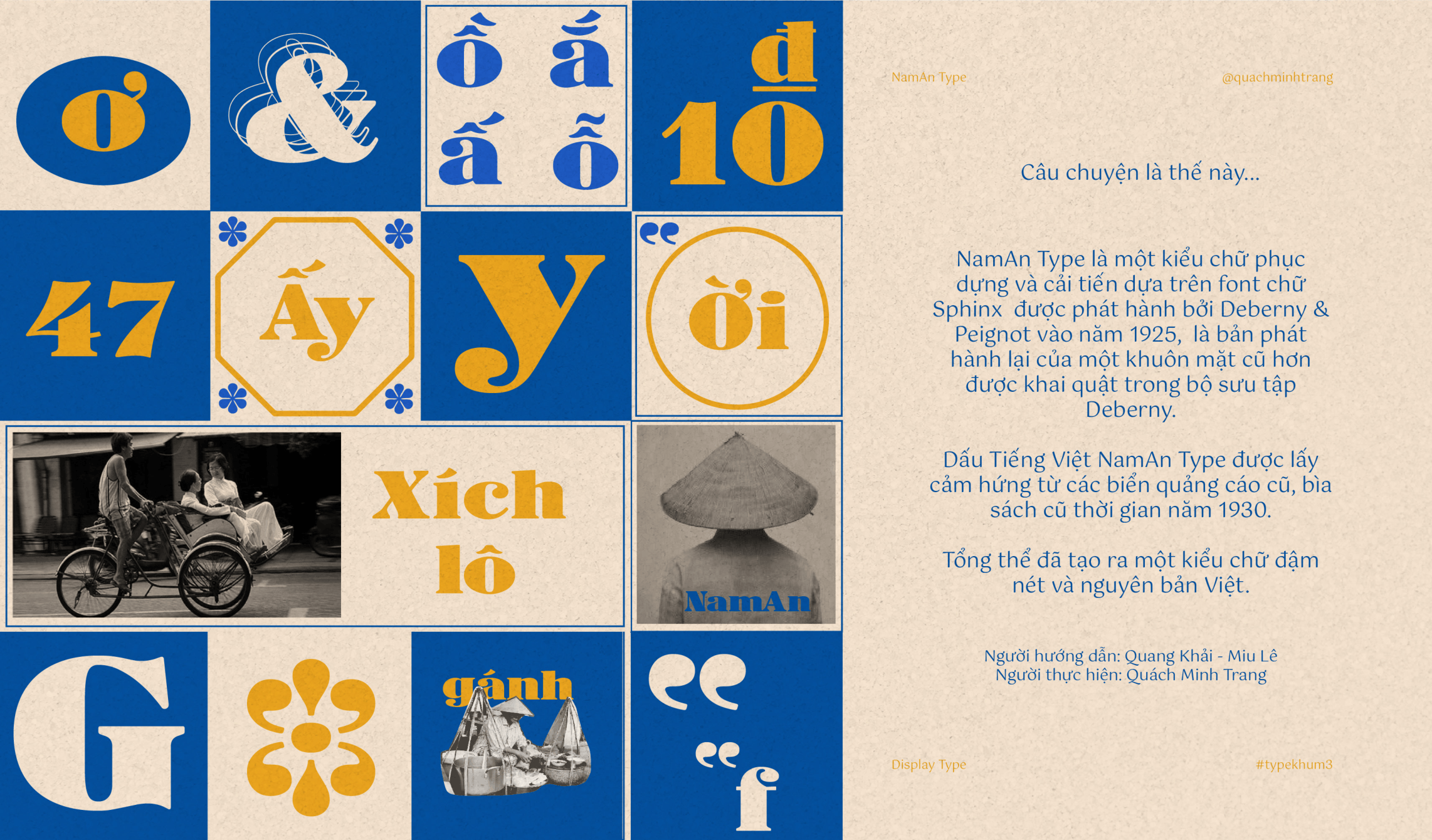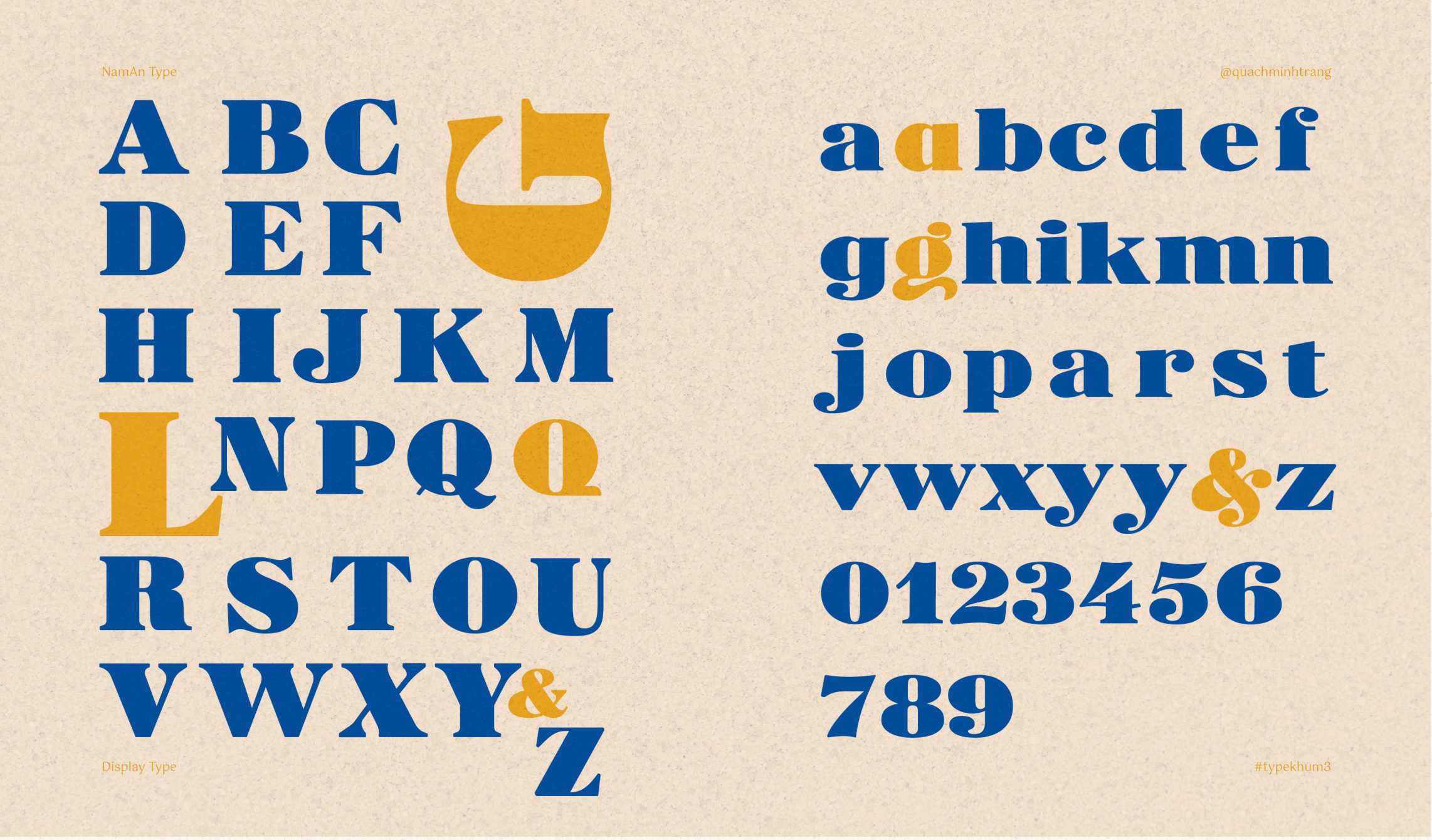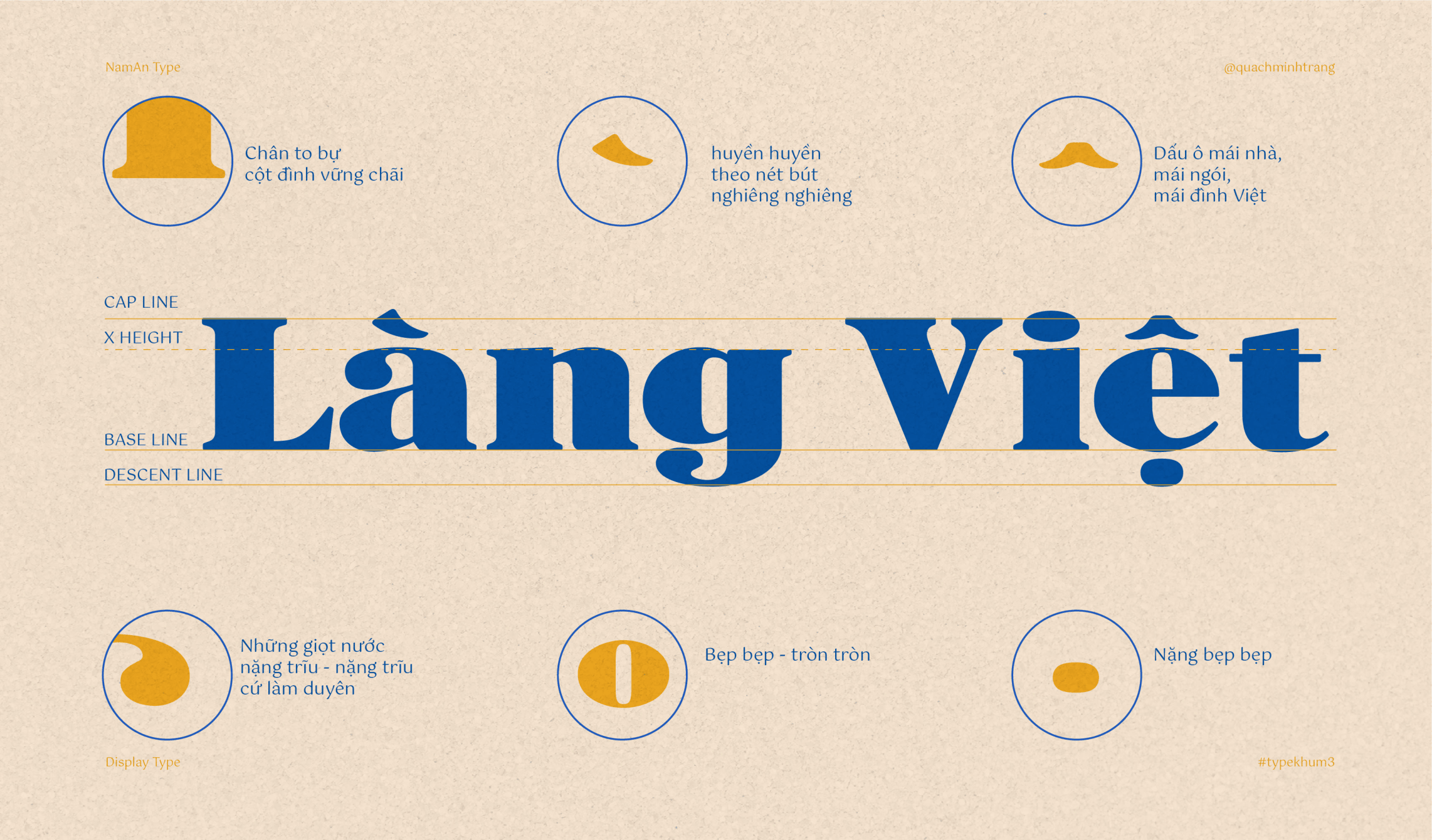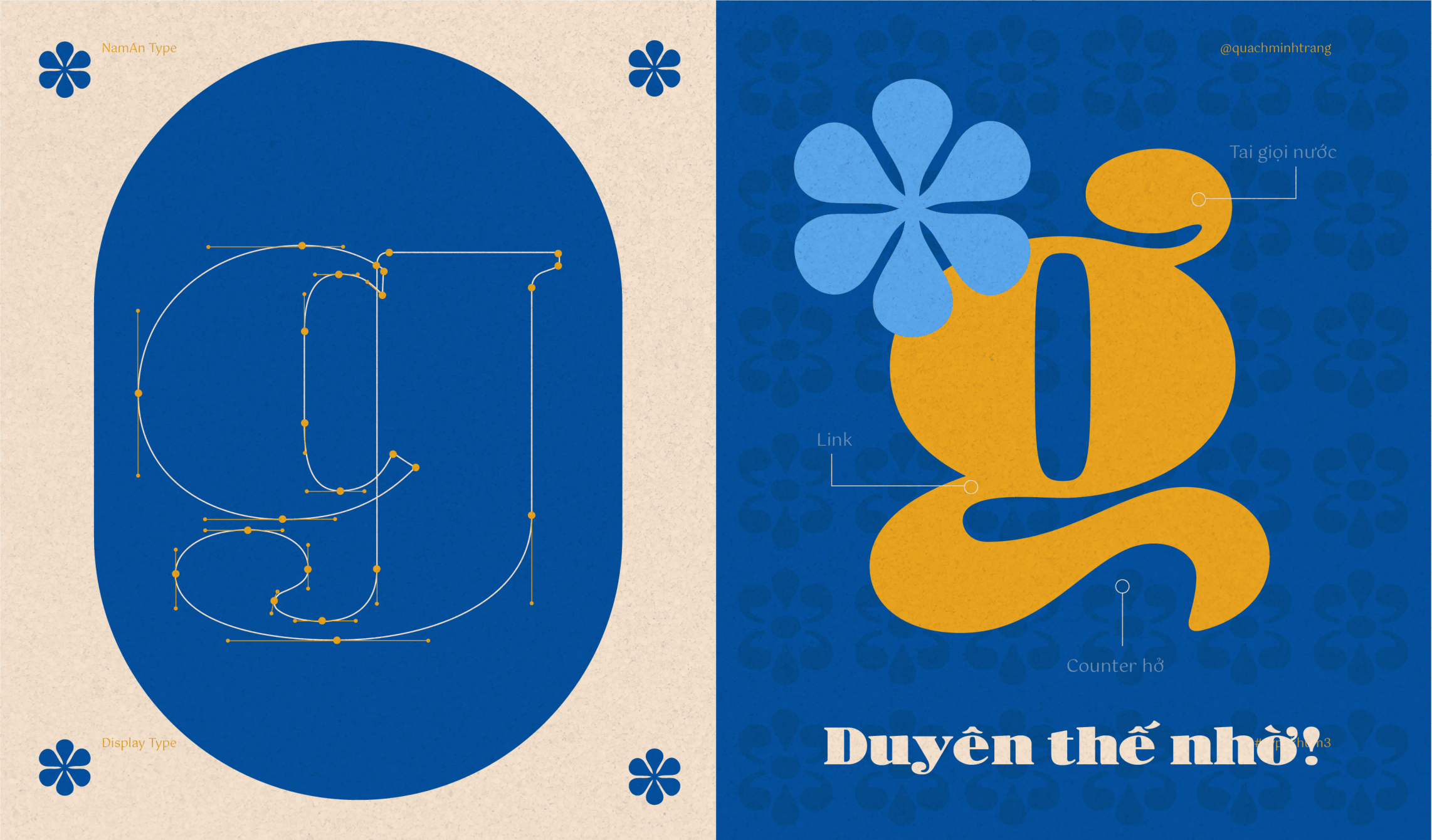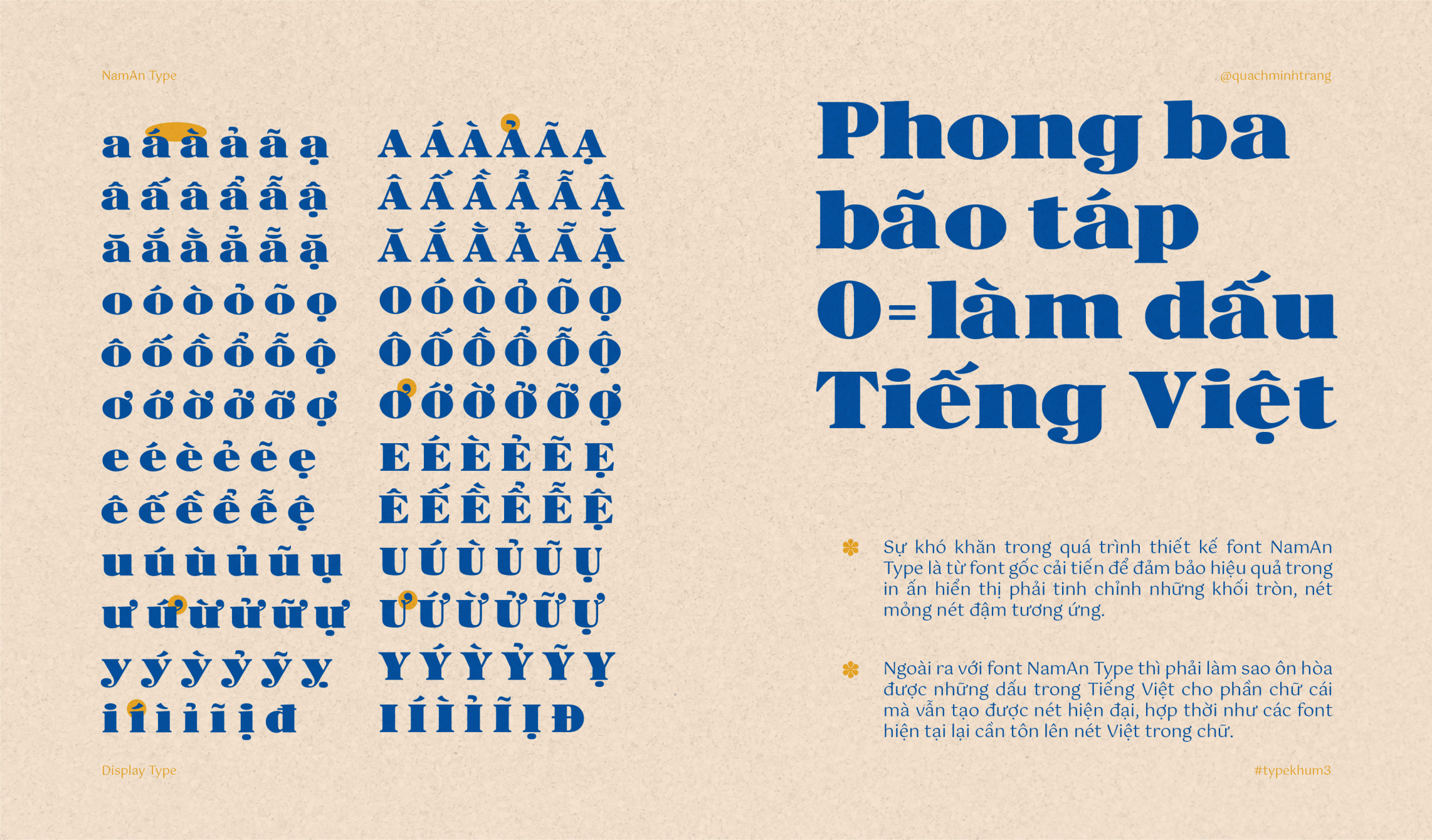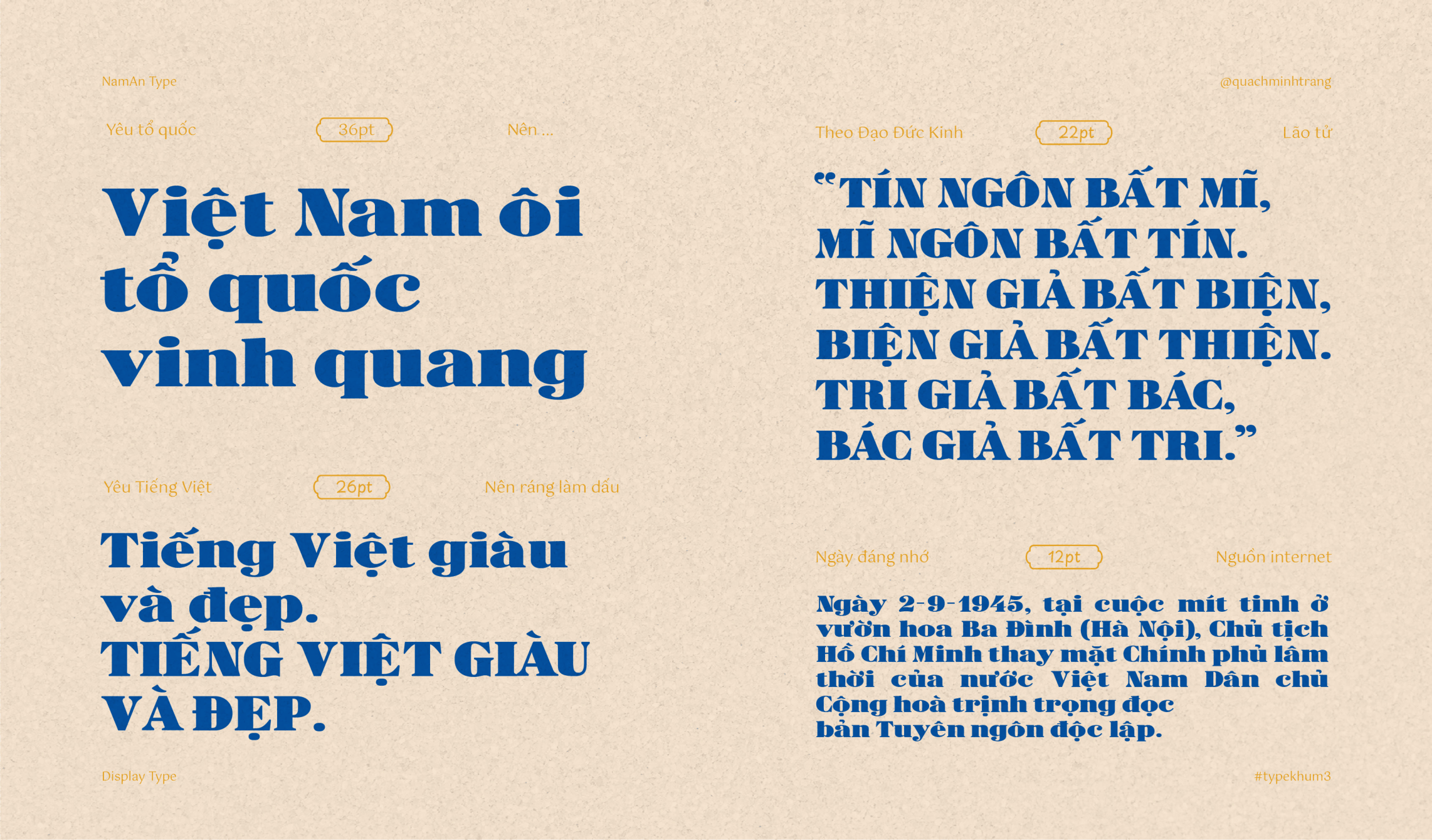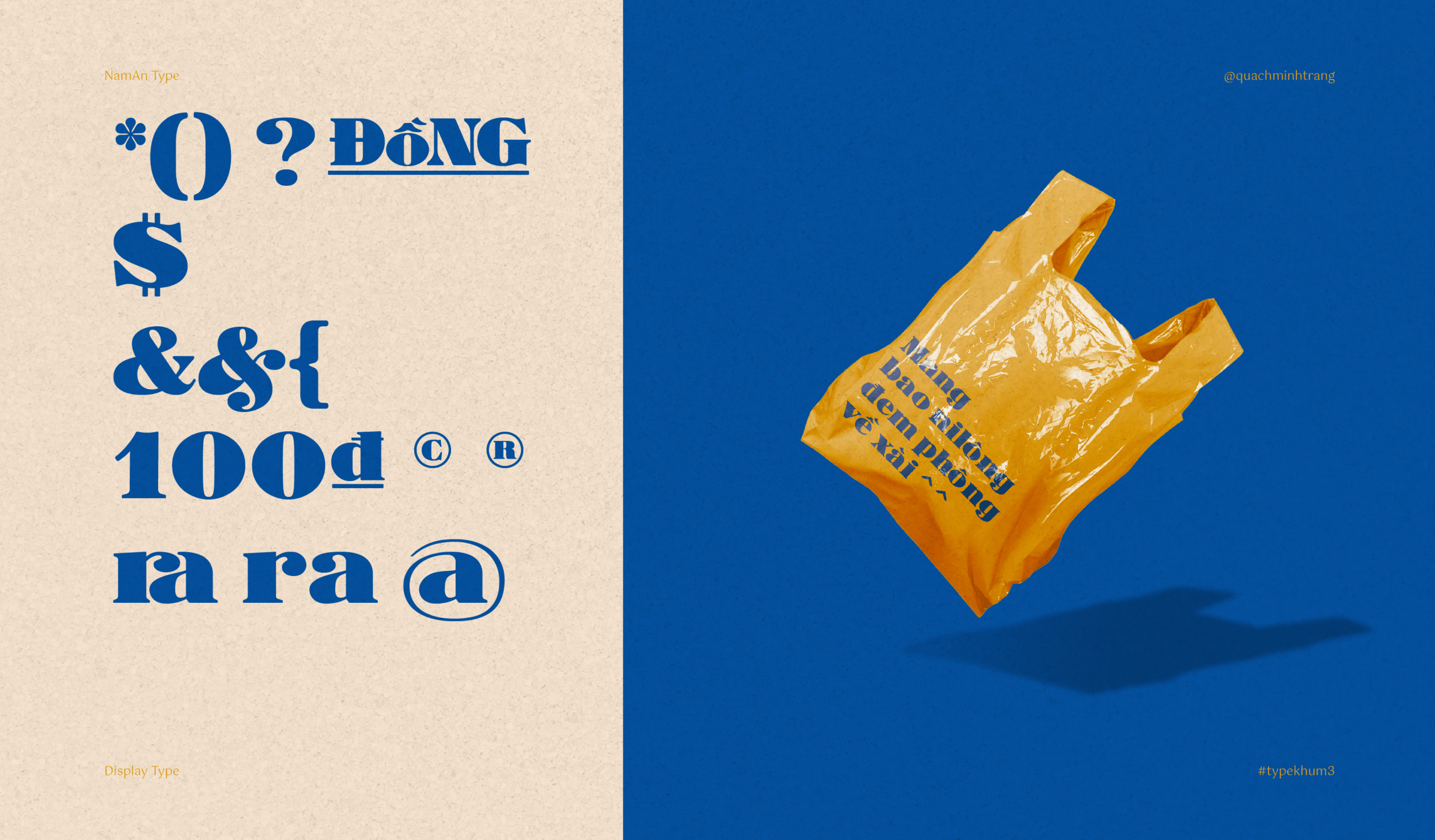
NamAn
Về NamAn: NamAn là một kiểu chữ phục dựng và cải tiến dựa trên font chữ Sphinx được phát hành bởi Deberny & Peignot vào năm 1925, là bản phát hành lại của một khuôn mặt cũ hơn được khai quật trong bộ sưu tập Deberny. Dấu Tiếng Việt NamAn được lấy cảm hứng từ các biển quảng cáo cũ, bìa sách cũ thời gian năm 1930. Tổng thể đã tạo ra một kiểu chữ đậm nét và nguyên bản Việt.
Quách Minh Trang